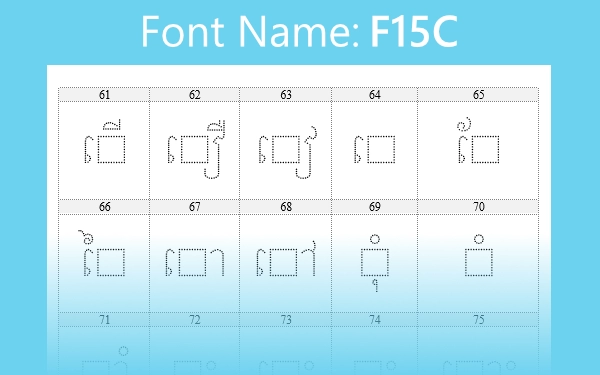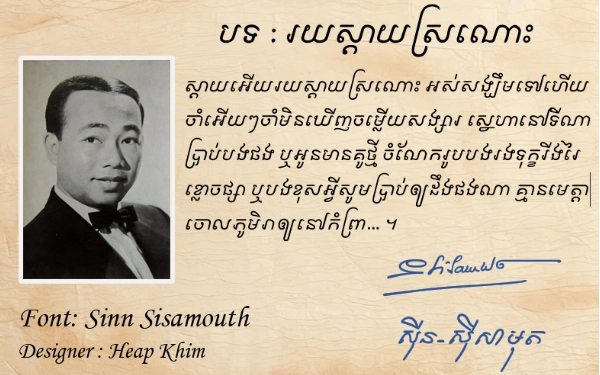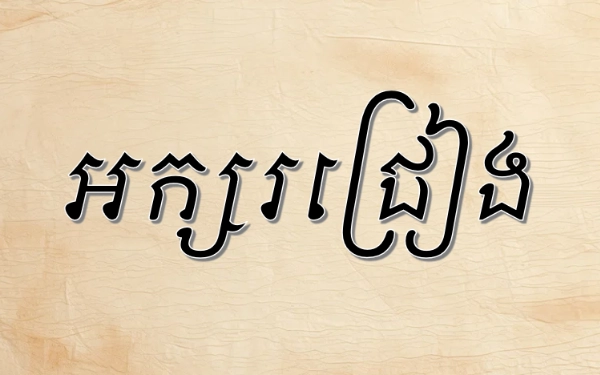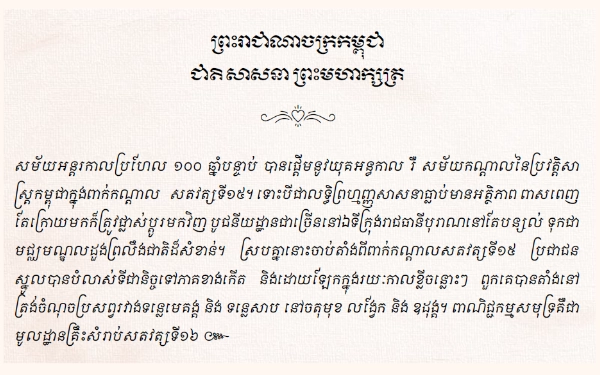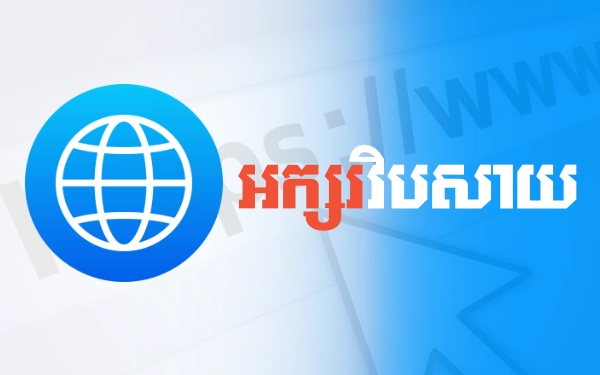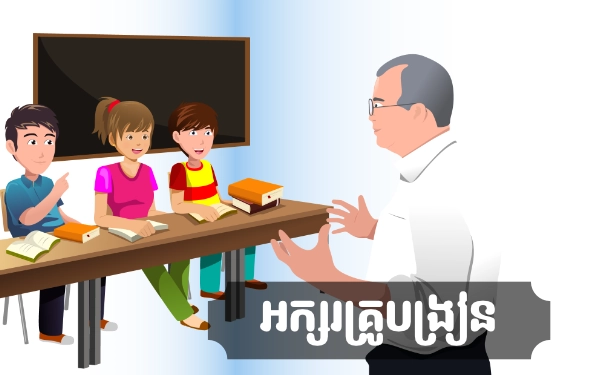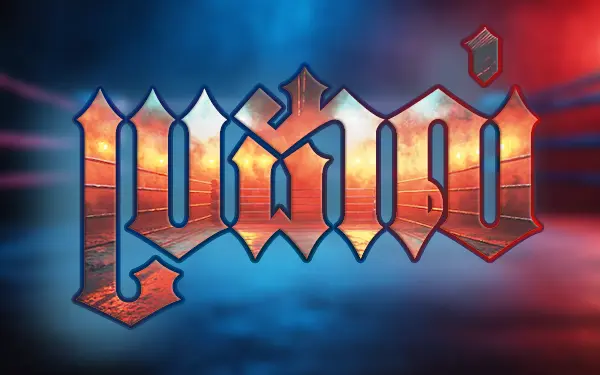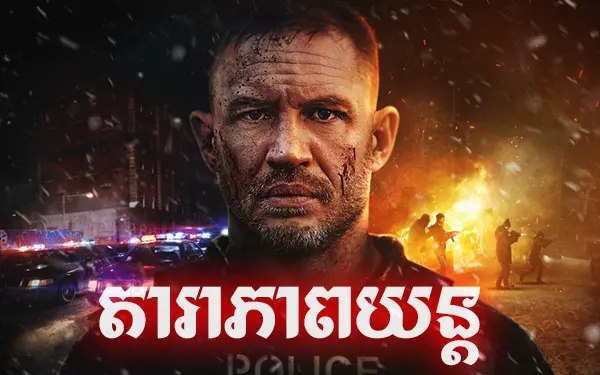
Font Design
Unicode Font Design
ព័ត៌មានបឋម
Khimsoft បានធ្វើការរចនាពុម្ពអក្សរទាំងអស់របស់ខ្លួនដោយឈរលើកត្តាសំខាន់ៗដូចបានបង្ហាញនៅខាងក្រោម ហើយការរចនាទាំងអស់នេះគឺមិនបានប្រើប្រាស់កម្មវិធីសម្រាប់រចនាដូចជា Adobe Illustrator, Corel Draw, Affinity Designer ឬកម្មវិធី Design ផ្សេងៗដើម្បីជាជំនួយឡើយ ។ យើងបានធ្វើការរចនារាល់ពុម្ពអក្សរបស់យើងដោយប្រើប្រាស់កម្មវិធីសម្រាប់រចនាពុម្ពអក្សរផ្ទាល់តែម្ដង ក្នុងនោះរួមមានដូចជា Font Creator និង Font Glyphs ឬ FontForge ។ អក្សរមួយចំនួនត្រូវការបន្ថែមកូដ ហើយអក្សរមួយចំនួនទៀតក៏ត្រូវការបន្ថយកូដទៅតាមទម្រង់នៃពុម្ពនីមួយៗ ។ លោកអ្នកប្រើប្រាស់ពិតជាមិនលំបាកដូចការរចនាឡើយ អ្នកជំនាញពុម្ពអក្សរទើបយល់អំពីបញ្ហាទាំងអស់នេះ ។
Font: Khimsoft MEF2
រូបភាពបង្ហាញពីអក្សរក្រោយពីបានរចនារួចសម្រាប់អក្សរ "ឈ"
ហើយនេះជារូបភាពនៅពេលរចនារួចរាល់ (ឃើញថាមិនមានឆែប)
រូបភាពបង្ហាញពីប្លង់នៅពេលរចនាសម្រាប់អក្សរ "ឈ"
រូបភាពអក្សរ "ម" នៅពេលស្ថិតក្នុងដំណាក់កាលរចនាលើកម្មវិធី
វត្ថុបំណងចាំបាច់
ពាក្យថា "កេរ្ដិ៍" នេះទៀតសោតក៏យើងបានគិតគូរផងដែរ ពោលគឺមិនឱ្យជើង "្ដ" ហើយនឹង "ិ៍" រត់ហួសពីអក្សរ "រ" ដូចគ្នា (គ្រប់ពុម្ពអក្សរទាំងអស់) ។
មួយទៀតពាក្យ ឌៀ ឌឿ ឬ ជឿ ផឿ ជាដើម គឺយើងបានជួយឱ្យស្រៈ "ៀ" និង ស្រៈ "ឿ" មិនដិតជាប់នឹងអក្សរ "ឌ" ផងដែរ ។
ចំពោះពាក្យ "វរ្ម័ន" យើងបានយកចិត្តទុកដាក់គ្រប់ពុម្ពអក្សរទាំងអស់ គឺមិនឱ្យជើងរបស់អក្សរ "ម" ដើរហួសពីអក្សរ "រ" ឡើយ (បានថែមកូដ) ។
ដូចគ្នាផងដែរ ពាក្យថា "ឱ្យ" ក៏ត្រូវបានយកចិត្តទុកដាក់ធ្វើយ៉ាងណាមិនឱ្យជើងនៃអក្សរ "យ" ដិតជាប់នឹង "ឱ" ឡើយ បានន័យថានៅពេលអ្នកវាយវានឹងបង្ហាញជើងអក្សរ "យ" ដែលវែងជាងជើង "យ" ធម្មតាជំនួសភ្លាមៗ ។
Khmer Latin Font & Design
អំពីពុម្ពអក្សរខ្មែរ-ឡាតាំង
Khimsoft Khmer-Latin ត្រូវបានរចនាឡើងសម្រាប់ប្រើប្រាស់តាមតម្រូវការជាក់ស្ដែង ។ សម្រាប់កម្មវិធីទាំងឡាយណាដែលមិនអាចគាំទ្រអក្សរប្រភេទយូនីកូដ នោះយើងតែងតែប្រើប្រាស់អក្សរប្រភេទ Limon ដូច្នេះ Khimsoft Latin គឺជាប្រភេទអក្សបែប Limon ដែរ ប៉ុន្តែវាមិនឈរឡើងប្លង់អក្សររបស់ Limon នោះទេ ។
ចំណុចខ្លះៗគួរយល់ដឹង
បើអក្សរ Limon អ្នកនឹងត្រូវវាយ ព+ា ទើបបានអក្សរ "ញ" ប៉ុន្តែយើងបានរចនាប្លង់អក្សរទាំងនេះឱ្យមានជាអក្សរ "ញ" និងចុចដូចគ្នានឹងខ្មែរយូនីកូដែរ គឺចុច Shift + J វានឹងចេញអក្សរ "ញ" តែម្ដង ។ ទាក់ទងនឹងត្រកូលអក្សរ "ញ" នេះដែរ អ្នកអាចមើលបន្ថែមនៅប្លង់ក្ដារចុច Khimsoft Khmer-Latin បន្ថែមទៀត ។
ដើមឡើយអក្សរយើងស៊ែរមុនៗមិនអាចវាជើង "្ហ" ជាមួយនឹងអក្សរ "ឡ" បានទេ ដូច្នេះហើយយើងឃើញថាប្រសិនបើអ្នកត្រូវការវាយពាក្យ "ទឡ្ហីករណ៍" នោះមុខជាជើងជើងអក្សរ "ហ" មុខជានៅជាន់នឹងអក្សរ "ឡ" មិនខាន ។ ដូច្នេះហើយយើងបានរចនាវាឡើងដោយតម្រូវឱ្យចុចលើ J + Shift + H តែប៉ុណ្ណោះ ។
ពាក្យថា "ឱ្យ" គឺយើងបានរចនាឱ្យដូចគ្នានឹង Khimsoft Unicode ដែរ គឺចុចលើសញ្ញាស្មើ (=) ហើយនឹង "បា" ឬ "ប៉ា" អក្សរនេះគឺមិនប្រើដូច Limon ដែលតម្រូវឱ្យអ្នកវា Shift + 0 រួចថែមស្រៈ "ា" ឬ "ៅ" នោះទេ លោកអ្នកគ្រាន់តែចុចលើអក្សរ "O" វានឹងចេញ "បា" តែម្ដង ។ សូមប្លង់ក្ដារចុច Khimsoft Latin បន្ថែម ។
ប្រសិនបើអ្នកត្រូវការវាយពាក្យថា "លក្ស្មី" (ព្រះនាងលក្ស្មី) នោះលោកអ្នកគ្រាន់តែចុចលើ J + ] បន្ទាប់ពីវាយជើង "្ស" រួចគឺជាការស្រេច តែអក្សរ Limon មិនមានទេ ហើយលោកអ្នកដែលបំពេញឈ្មោះស្តង់ដារសម័យលីមូន ហើយមាន ឈ្មោះថា លក្ស្មី គឺត្រូវវាយតាមជាក់ស្ដែងដូចជា ល+ក+ុ+្ស+ី តែអក្សរយូនីកូដមិនអាចវាយខុសបែបនេះបានទេ ។
សញ្ញា និង វណ្ណយុត្តិ
អ្នកអាចវាយសញ្ញាពិសេសៗបានច្រើនដូចជា ម៉ែត្រការ៉េ គោមូត្រ កុក្កុដនេត្រ សញ្ញាបូក ដក គុណ ចែក បានពេញលេញ (មើលប្លង់ក្ដារចុចបន្ថែម) ។
ចំពោះការប្រើប្រាស់សញ្ញាវណ្ណយុត្តិខ្មែរ គឺយើងបានរចនាឡើងឱ្យដូចគ្នាទាំងស្រុងជាមួយនឹងអក្សរខ្មែរយូនីកូដ ។ ការធ្វើបែបនេះដើម្បីសម្រួលកាន់តែលឿនឡើងសម្រាប់លោកអ្នកដែលចេះវាយអក្សរយូនីកូដរួចហើយមិនពិបាកក្នុងការចំណាំង និវាយអក្សរប្រភេទ Khimsoft Latin ។
យើងបានរចនាឱ្យមានរូបិយប័ណ្ណ រៀល និងដុល្លារ រួមទាំងលេខខ្មែរ និងឡាតាំងសម្រាប់សម្រួលដល់ការប្រើប្រាស់បានយ៉ាប្រសើរ (គ្រប់ពុម្ពអក្សរឈុតខ្មែរ-ឡាតាំងទាំងអស់ ។
នៅពេលដែលអក្សរត្រកូល "ញ" ត្រូវបានរៀបចំឱ្យនៅក្នុង Block អក្សរត្រឹមត្រូវ នោះវាមើលទៅគឺពិតជាអក្សរ "ញ" ច្បាស់លាស់ មិនមែនយកអក្សរ "ព" ហើយថែមស្រៈ "ា" ធ្វើជាអក្សរ "ញ" ទៀតឡើយ ។ ការធ្វើបែបនេះគឺងាយស្រួលច្រើនសម្រាប់ការរៀបចំពុម្ពអក្សរឈុតនេះចេញពីអក្សរដែលមានស្រាប់ ។